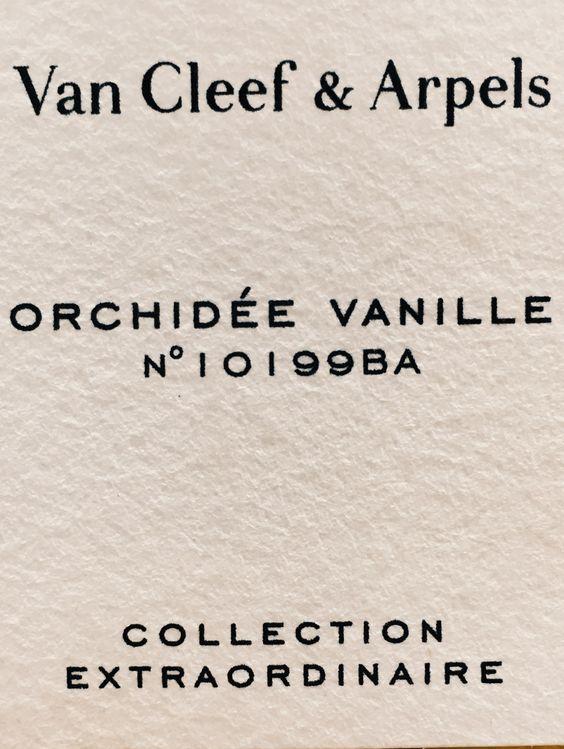
Suche Schrift von der Marke VAN CLEEF & ARPEL auf der Parfumflasche
ich bin auf der  Suche der oder ähnlichen Font. Sie darf auch gerne etwas kosten.
Speziell suche ich die Schrift des Textabschnittes auf dem Bild "ORCHIDÉE VANILLA N° 10199BA". Den besonderen Fokus der Schriftart lege ich auf die Buchstaben "R",  "E" (mit seinem kurzen Mittelstrich) und die Zahl 1 (die fast nahezu nur als Strich geschrieben wird). Ich recherchiere bereits eine ganze Weile, komme aber leider bisher auf ein noch nicht zufriedenes Ergebnis.
Das Label `Van Cleefs & Arpels` kommt aus der Kosmetikindustrie und die Flacons kann man auch hier noch einmal sehen https://www.vancleefarpels.com/eu/de/la-maison/fragrances/Collection-Extraordinaire-inspirations.html?55click=Highlight
suche mal nach folgenden Schriften:
Engarvers Gothic BT (bei Corel-Produkten wie Draw mitgeliefert)
Sackers Gothic